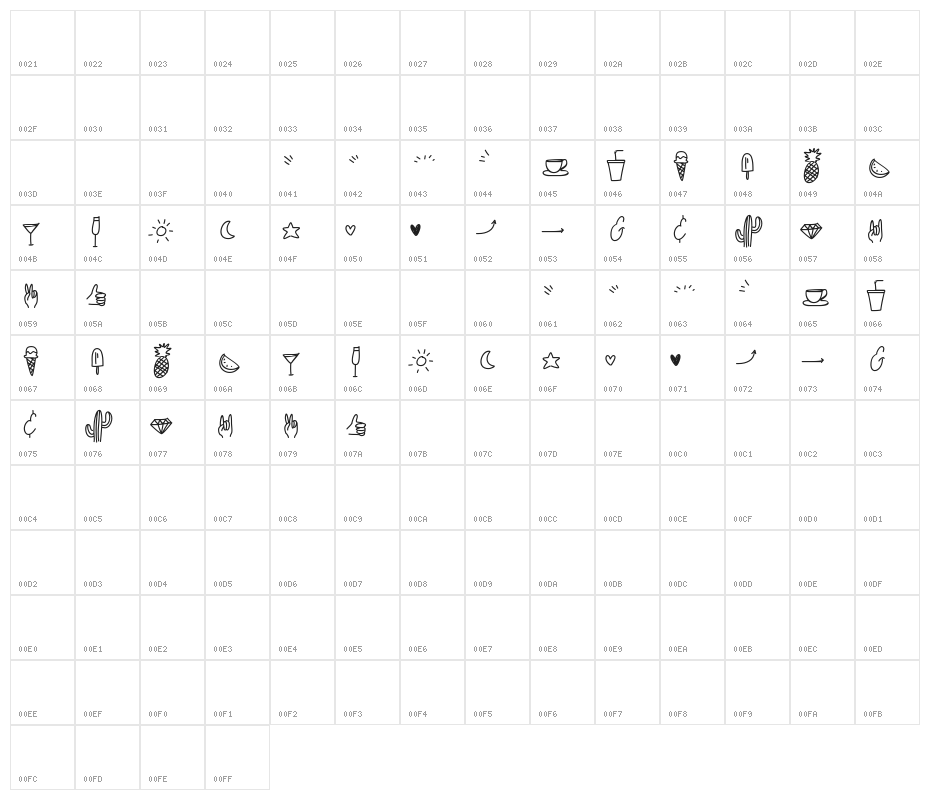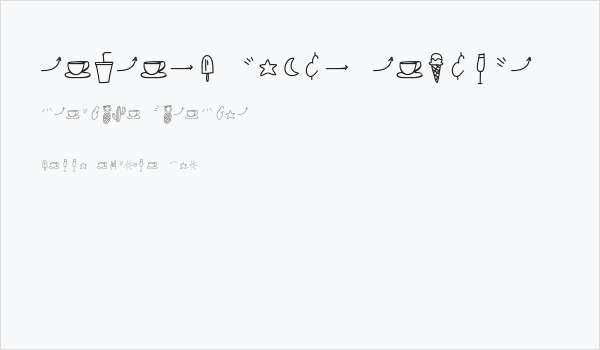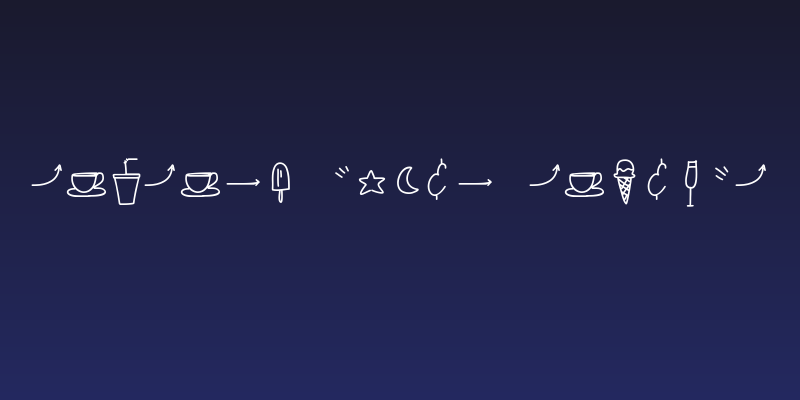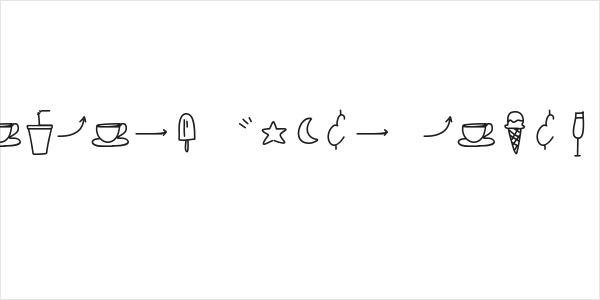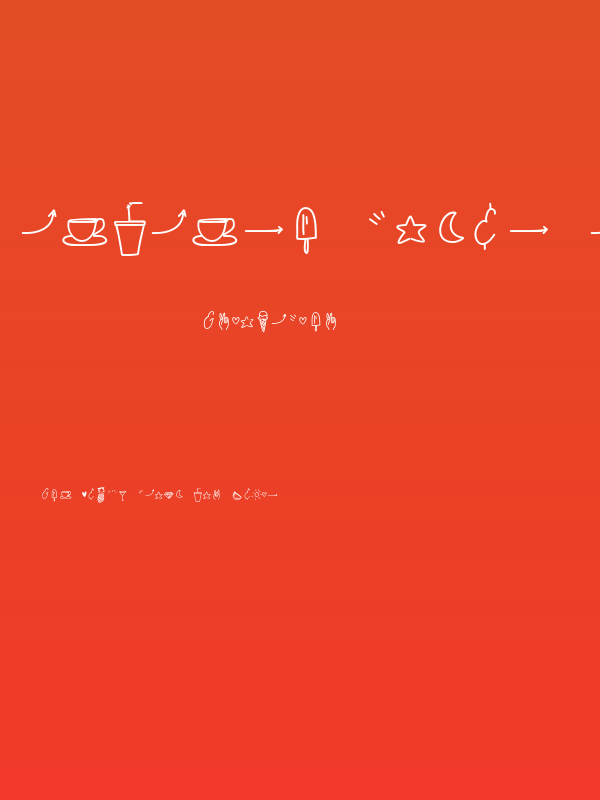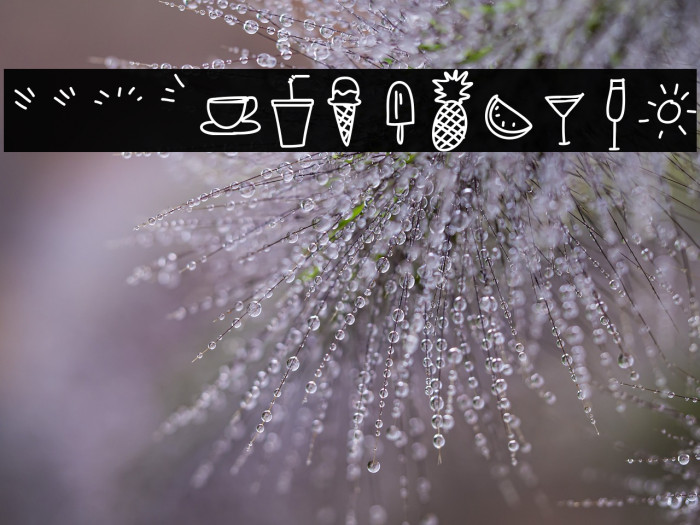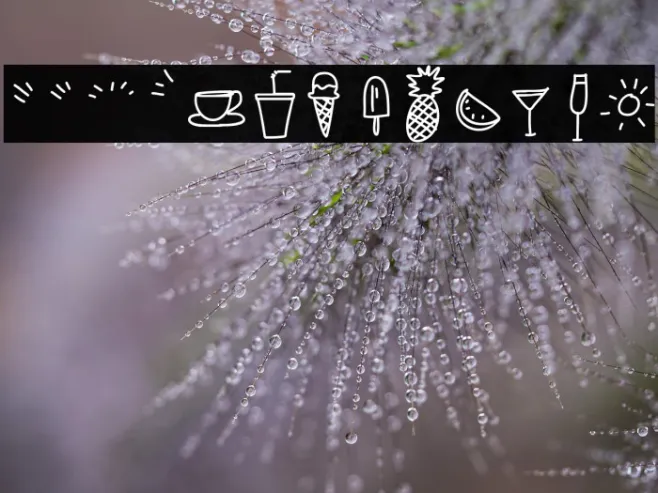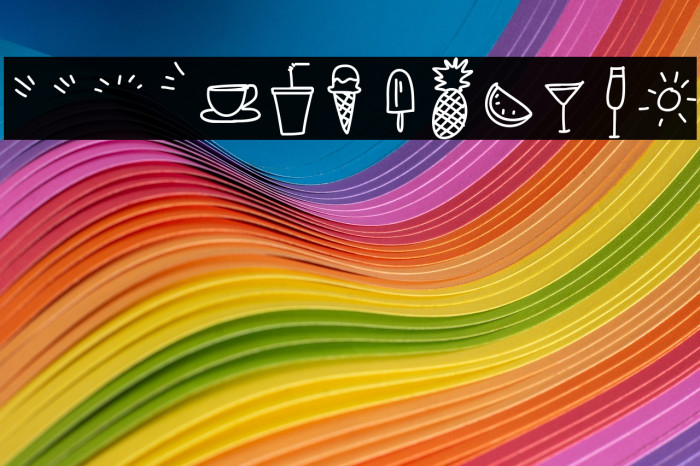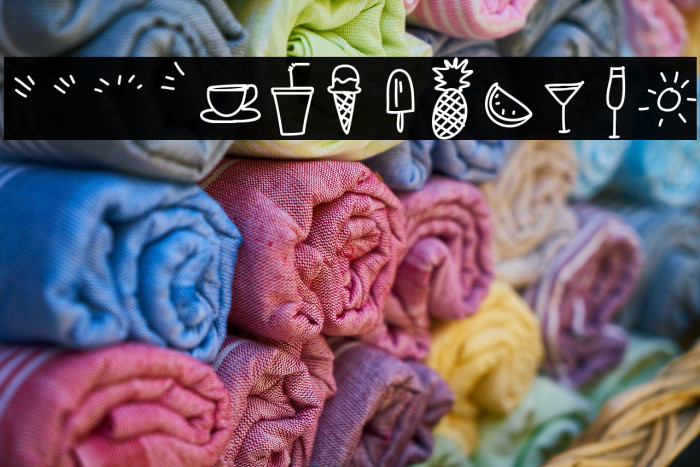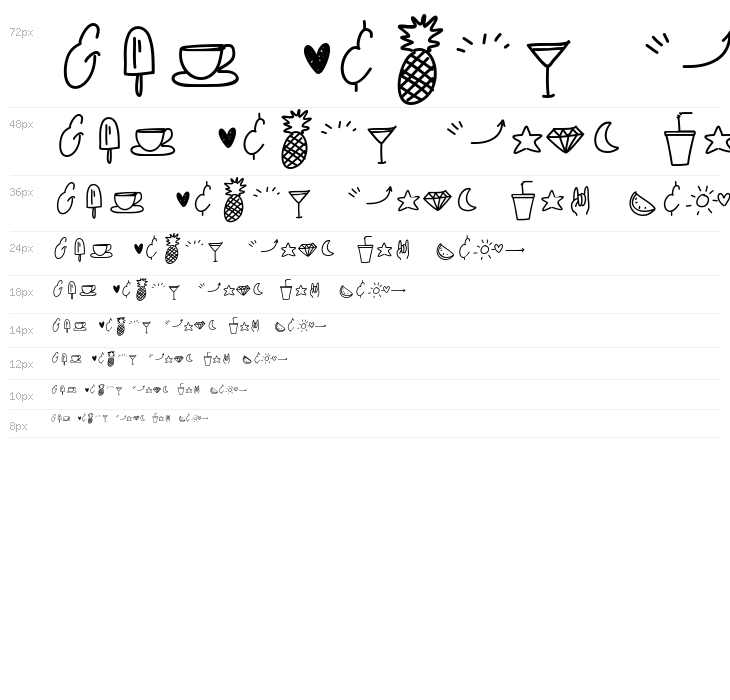
Refresh bonus Regular Font
✎ Dingbats
| Stil general | Whimsical |
| Caz de utilizare | Decorative elements, Illustrations, Craft projects |
| Proiecte propuse | Ideal for use in children's books, casual invitations, social media graphics, and DIY craft projects. |